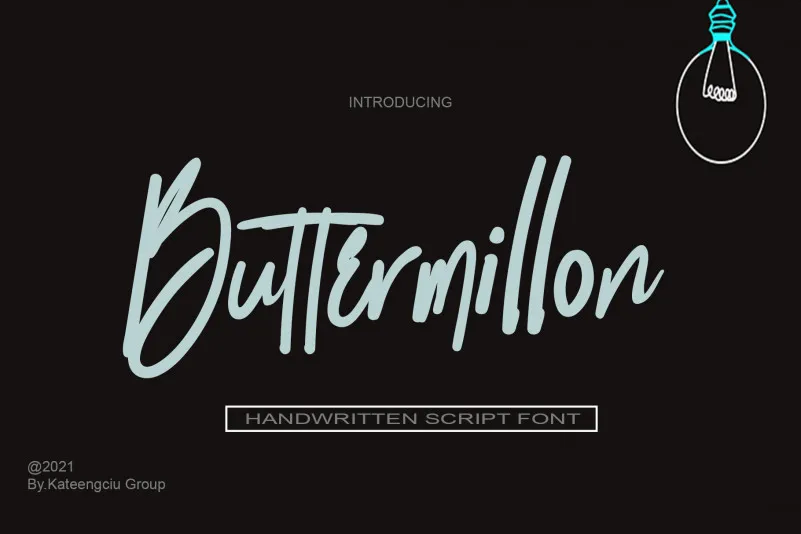
Buttermillon Script Font – Download Grátis
A fonte Buttermillon Script é uma escolha perfeita para quem busca uma mistura única de sofisticação clássica e modernidade atual. Ela mantém fielmente sua influência de escrita tipográfica, mas se destaca com um toque fresco que a torna ainda mais contemporânea. Seu caráter versátil permite-lhe atender ao vasto espectro de ideias criativas do mundo das letras e papelaria. De carteirinhas e títulos até papéis de presente, essa fonte tem o potencial para se adaptar a muitas necessidades. Ideal tanto para designers gráficos quanto para pessoas que buscam uma maneira única de expressar suas ideias pessoais, a Buttermillon Script é um recurso indispensável no arsenal de qualquer artista visual. Suavemente fluida e bem-sequenciada, ela oferece a perfeita combinação de elegância e frescura para criar um design que seja tanto uma obra de arte quanto funcional.